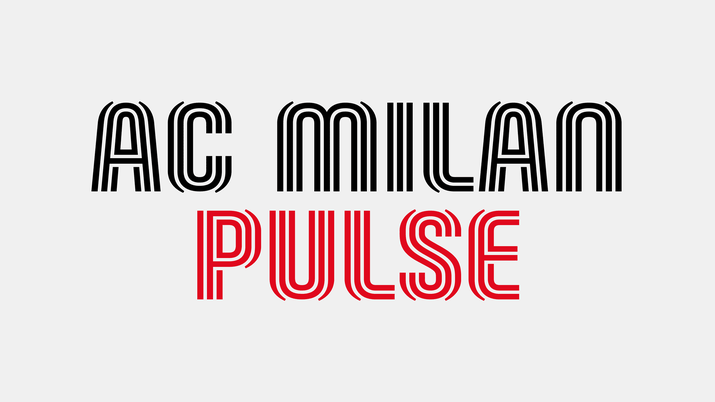
ULTIME MILAN – La collaborazione tra DixonBaxi e il grafico Elliott ha fatto nascere il nuovo font del Milan. Ecco le parole della nota agenzia di Londra sul proprio sito web: “Abbiamo collaborato con il grafico Elliott Amblard per sviluppare e realizzare ‘Milan Pulse Inline’, un carattere tipografico su misura per l’AC Milan. Prendendo spunto dalla moda, dai marchi di lifestyle e dalla cultura italiana, abbiamo creato un sistema tipografico audace ma elegante. Immediatamente riconoscibile, cattura la passione che i fan di Milano hanno per il loro club”. Intanto, ecco le principali notizie di oggi per i rossoneri: continua a leggere >>>